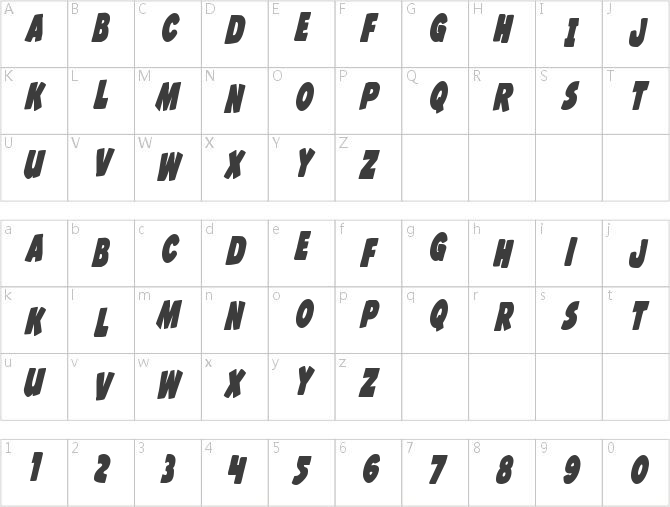
Jack's Candlestick Bold Extra-c
Jack's Candlestick Bold Extra-c介紹
Jack's Candlestick Bold Extra-c字體字庫是一款讓人賞心悅目、百看不厭的英文字體,適合各類廣告和產品包裝設計應用,字體大小0.07MB,格式為ttf字體,上傳用戶是xqy,作者/版權方為未知